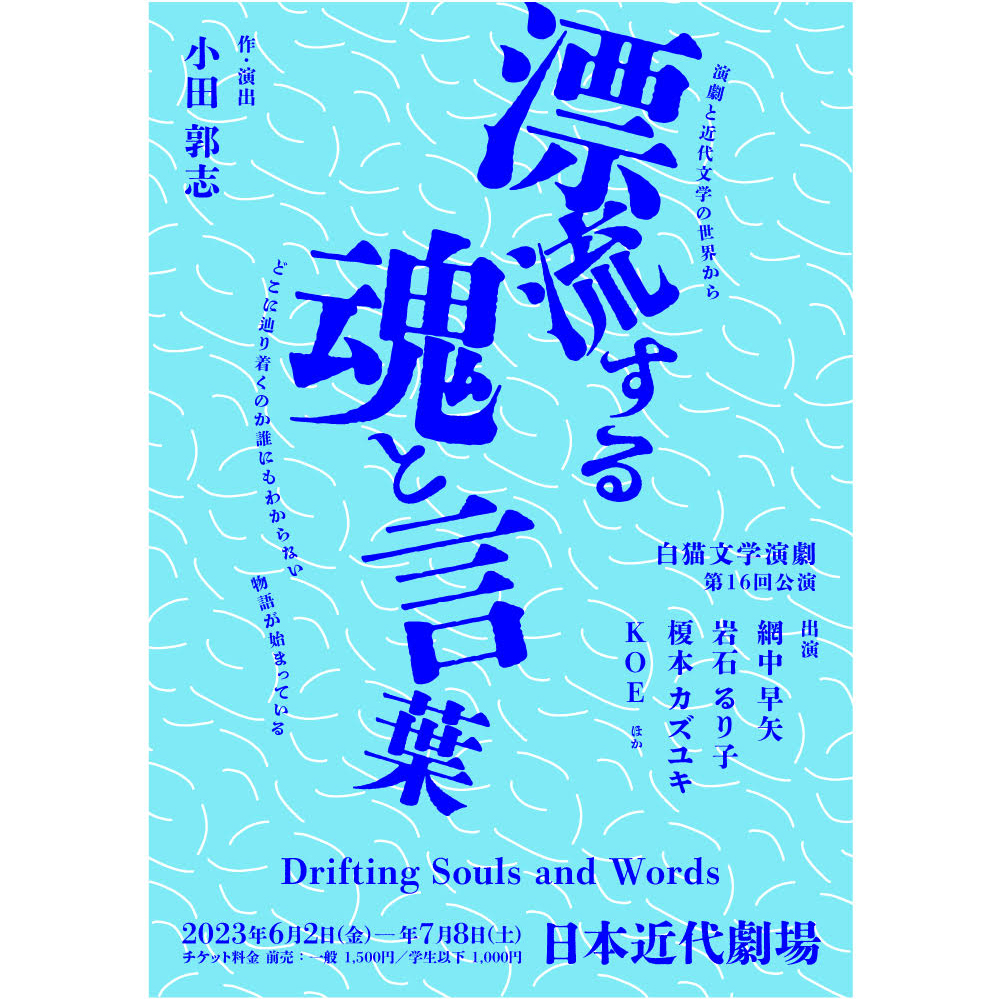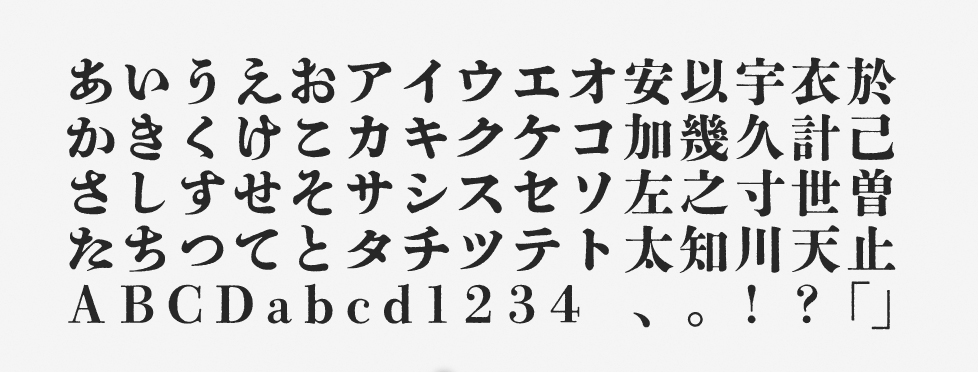
「秀英にじみ四号太かな」について
秀英にじみ四号太かなは、2022年10月に提供が開始されたフォントです。平仮名と一部の記号類のみであった「秀英四号太かな」に、「秀英にじみ初号明朝」の漢字が組み合わせられています。ベースとなった「秀英四号太かな」は、大日本印刷の金属活字「秀英四号明朝太かな」を復刻した書体です。
「秀英にじみ四号太かな」の特徴
ひらがなには太い筆で書かれたような力強いうねりがあり、クセの強さや重量感を与えつつ、見出しなどをしっかり強調できます。かな、漢字、英数字があらかじめ揃えられているため、合成フォントの作成の手間もかからずにスムーズに使えて便利です。
デザイン面の大きな特徴として、活版印刷に特有のインクの滲みが再現されています。雰囲気のある世界観を作り出すことができ、紙媒体はもちろん、Webや映像制作の現場でも有効です。
このフォントの滲み加工は絶妙で、アナログらしさのある “墨溜まり” も表現されているため、独特な味わいが出ています。秀英シリーズはファミリーもたくさん増えてきており、常に愛用しているフォントです。今回の作例ではタイトル部分の文字をバラバラにレイアウトし、 “漂流している雰囲気” を演出しました。